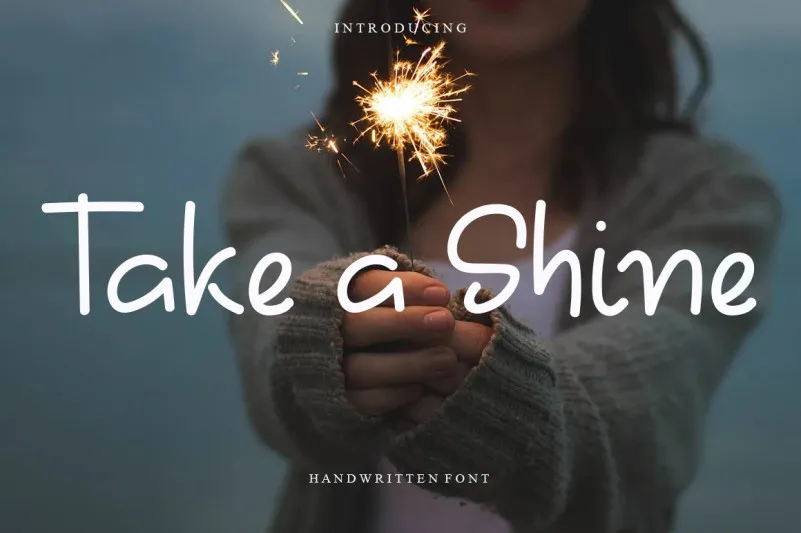
Take A Shine Font – Fonte Grátis
Take A Shine Font
Esta é uma fonte script minimalista. Ela se destaca por sua estilo único e eterno que traz beleza à qualquer design. Use-a para criar designs espectaculares! A Take A Shine Font oferece a oportunidade de revolucionar os seus trabalhos gráficos, seja em projetos digitais ou impressos. Escolha essa fonte para aquecer suas criações com um toque versátil e emocionante. Que tal experimentar este novo recurso gráfico?